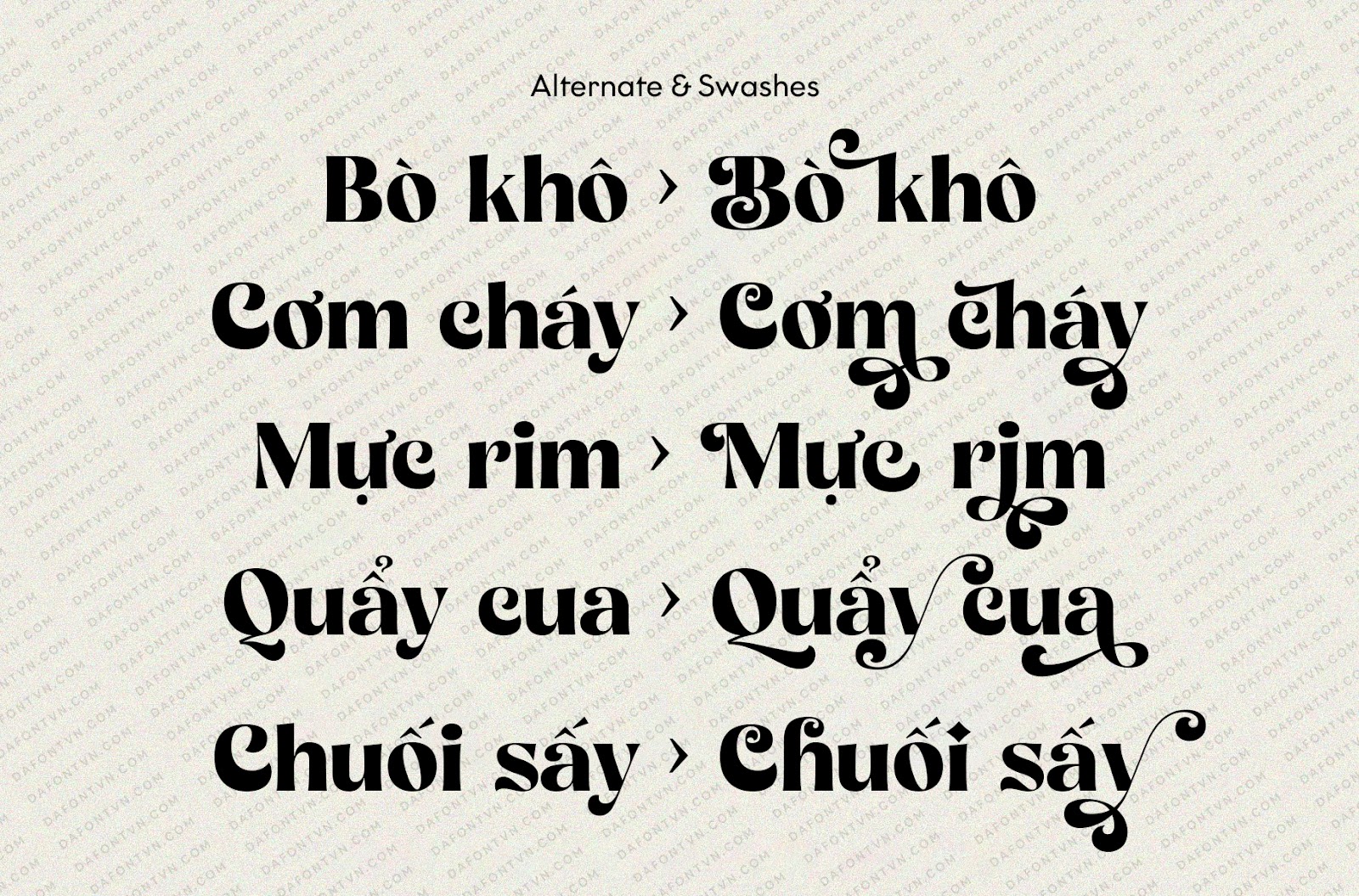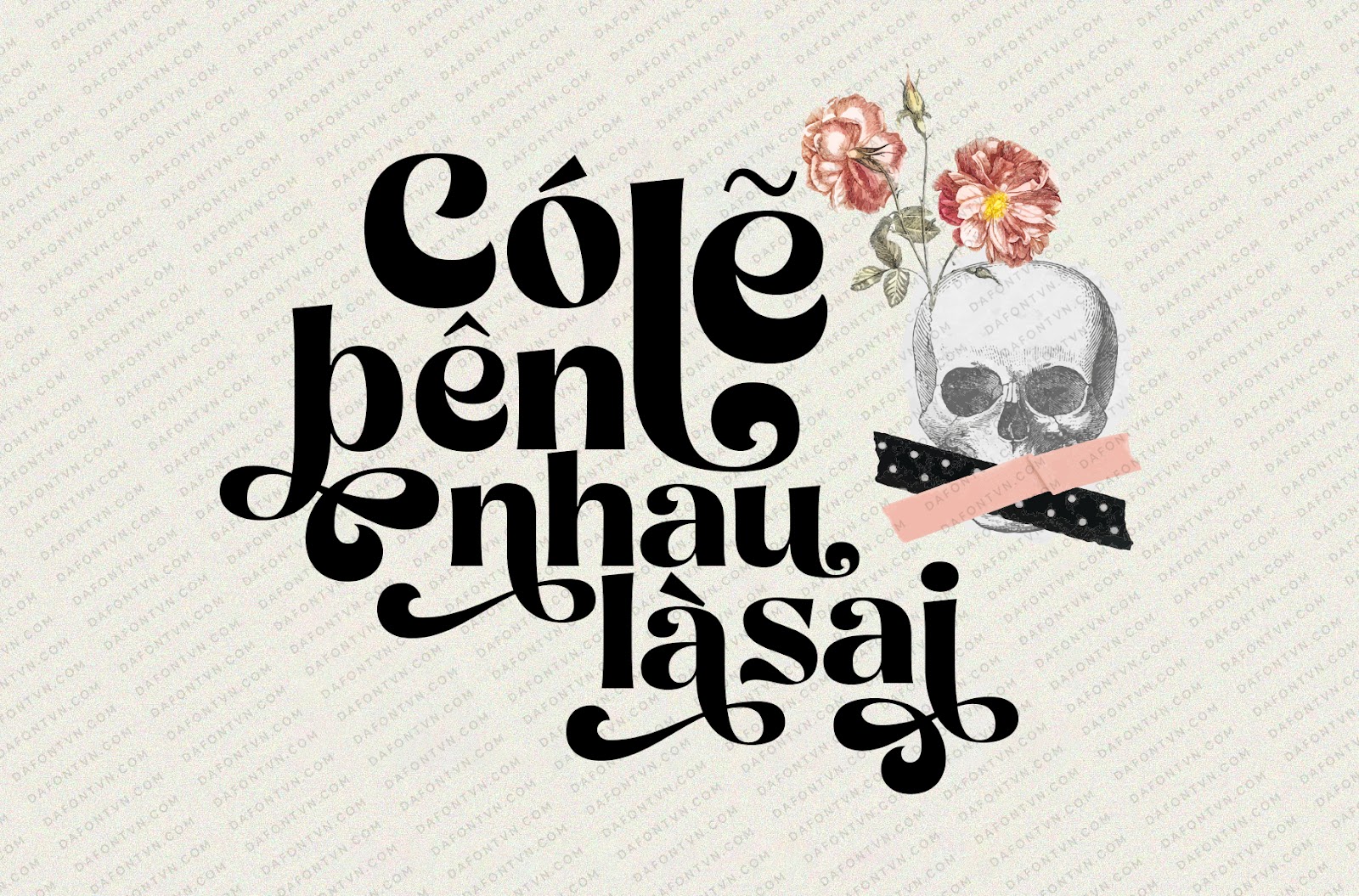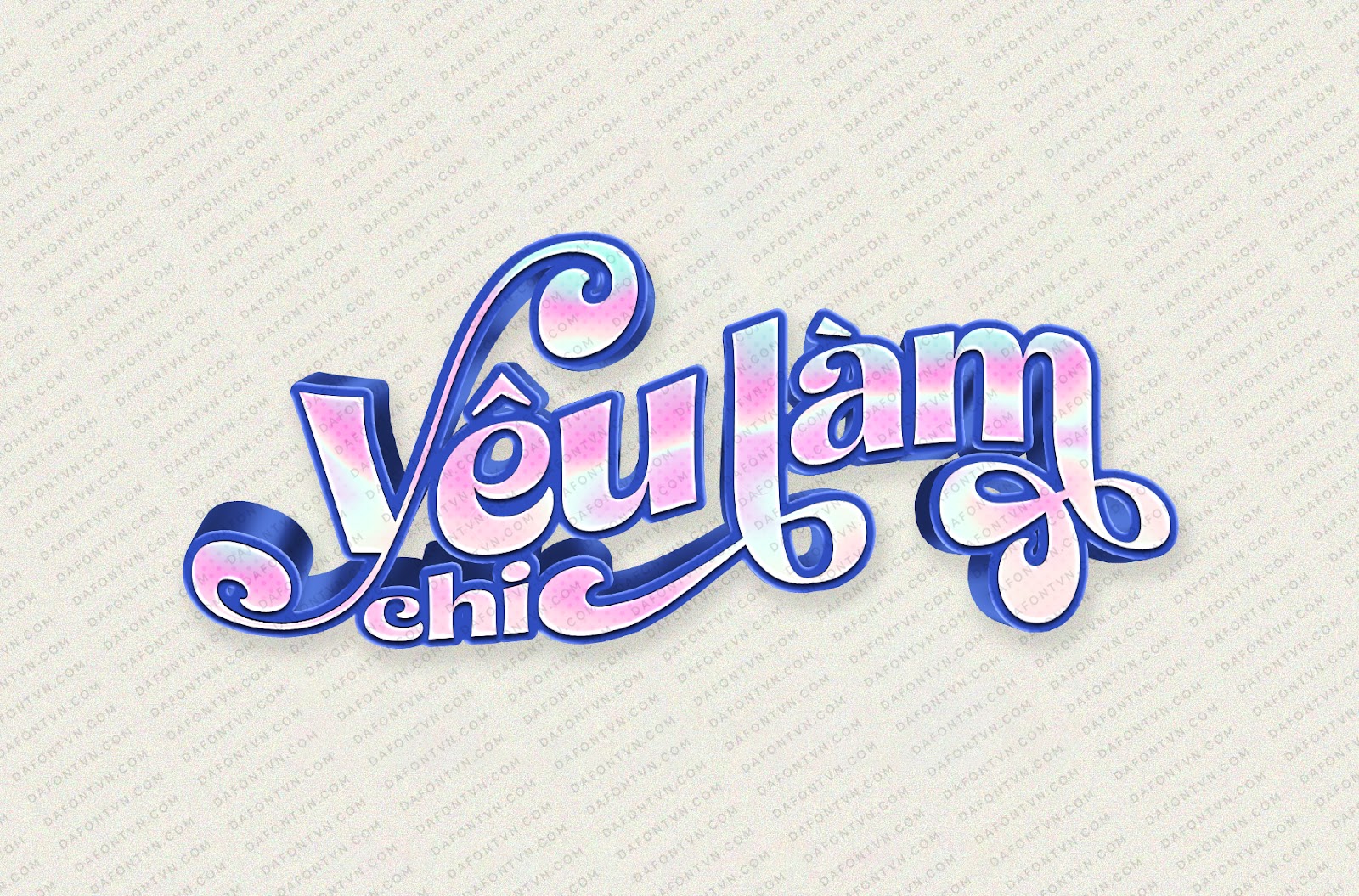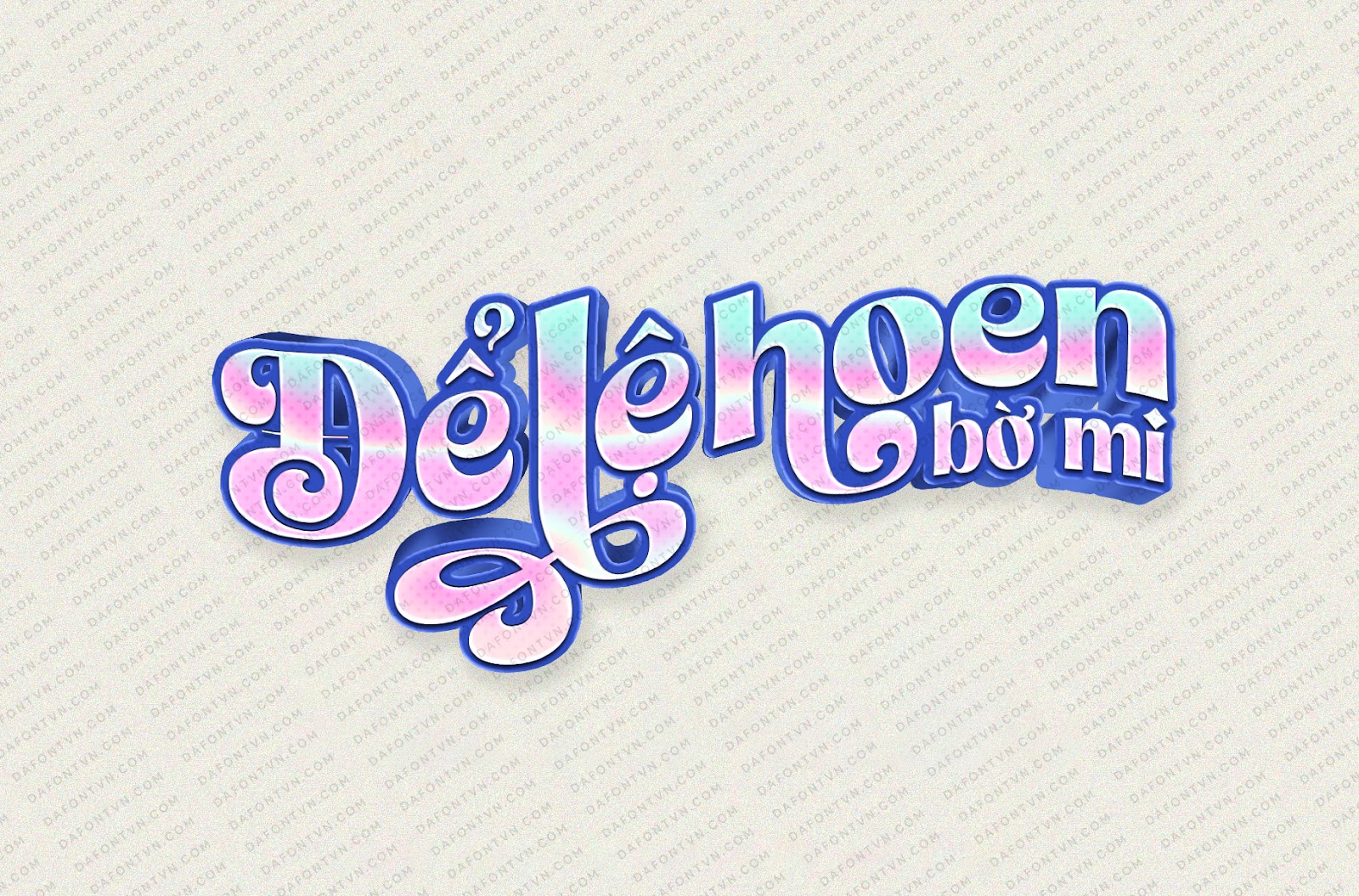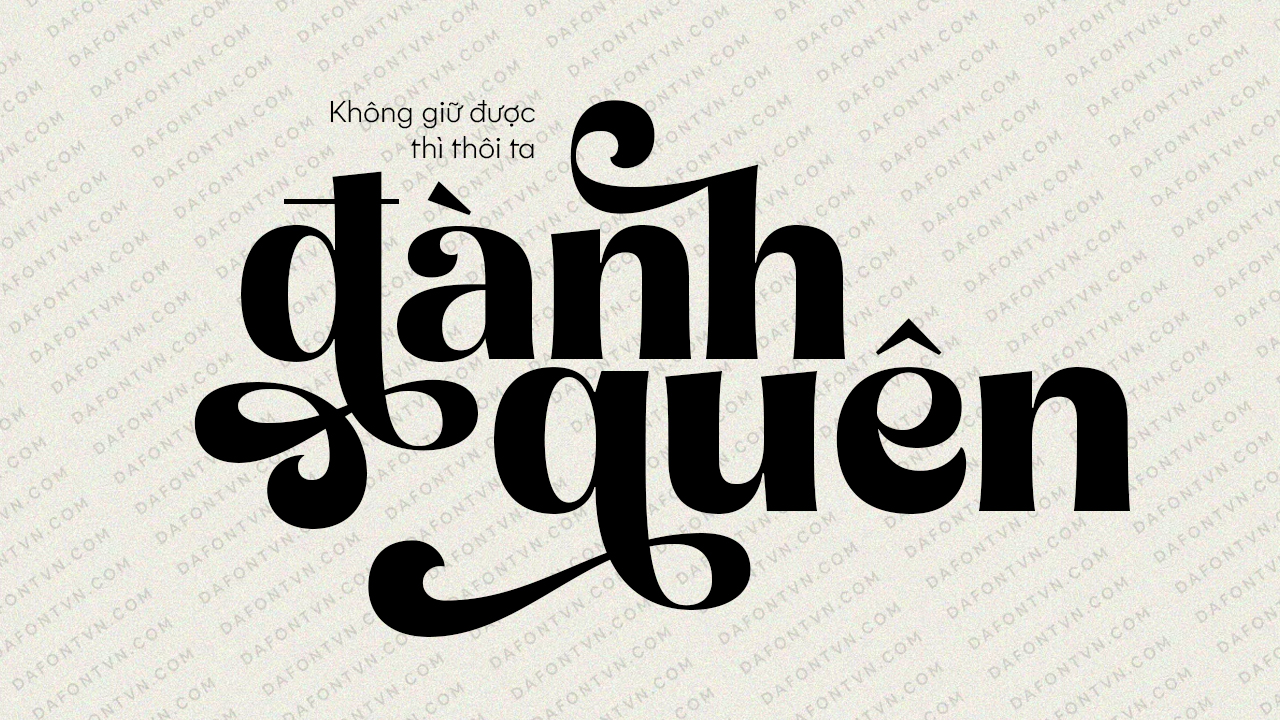
Bropella font là một kiểu sans táo bạo bao gồm alternates và swashes độc đáo.
Bropella đi kèm với phong cách cổ điển và hiện đại, các nét chữ được thiết kế nét đậm trông mạnh mẽ và nổi bật. Phông chữ này hoàn hảo cho tiêu đề, biểu tượng, thời trang, thương hiệu, bao bì, tạp chí…